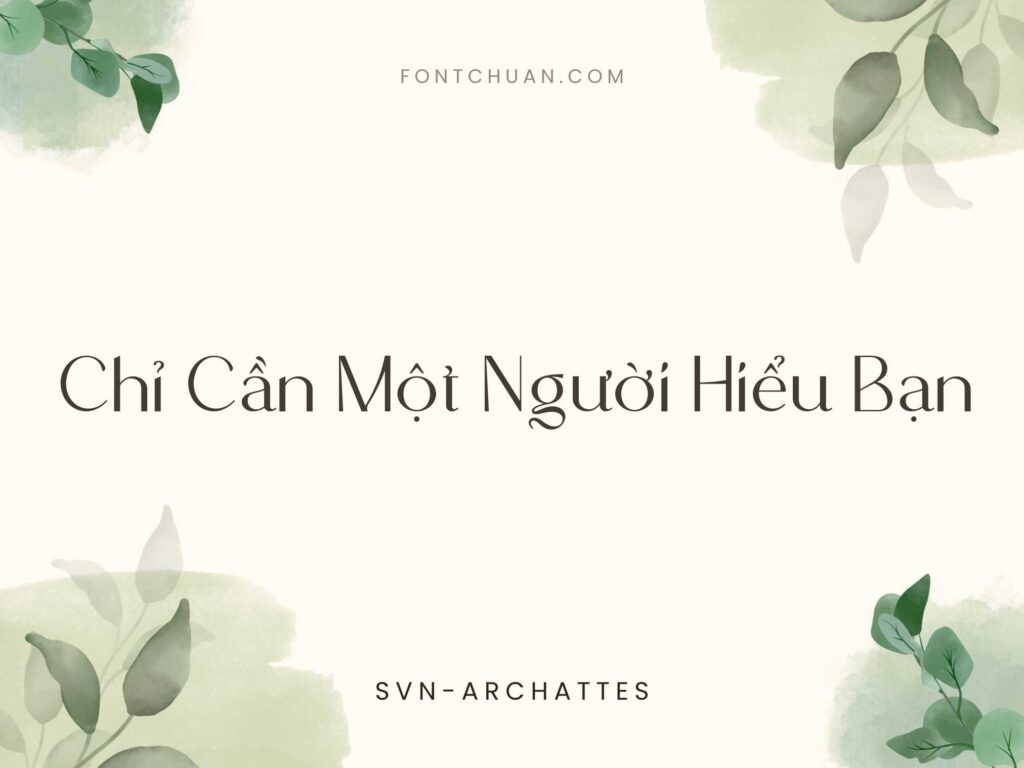
Font SVN Archattes Việt Hóa
Tác giả Font: Hayinah
Archattes là một font chữ sans-serif thanh lịch và đẹp mắt, được thiết kế để nâng tầm nhiều ý tưởng sáng tạo, từ thiệp mời đến xây dựng thương hiệu, nhãn mác và nhiều ứng dụng khác. Font này mang đến sự tinh tế và hiện đại cho các thiết kế, giúp tạo nên ấn tượng chuyên nghiệp và thu hút. Font đã được Việt hóa để hỗ trợ tiếng Việt bởi Styleno.1 Fonts, đồng thời hỗ trợ nhiều ngôn ngữ khác, mở rộng phạm vi sử dụng trên toàn cầu. Font này được thành viên của Font Chuẩn sưu tầm và chia sẻ, đáp ứng nhu cầu của bạn đọc và ứng dụng thực tế vào các dự án thiết kế.
Đặc điểm thiết kế của Archattes bao gồm các đường nét sạch sẽ, cân đối và dễ đọc, phù hợp cho các ứng dụng như thiết kế logo, nhiếp ảnh, nhãn mác và nhiều dự án sáng tạo khác. Các ngành nghề phù hợp bao gồm quảng cáo, thiết kế đồ họa và xây dựng thương hiệu.